Строение шрифта
В данной статье приведён список основных элементов типографских шрифтов, а также важнейшие характеристики.
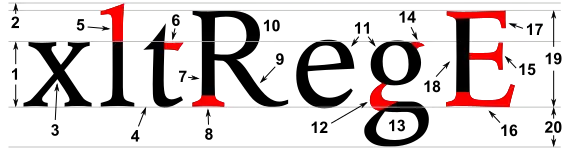
Линии
Через любую строку текста можно провести несколько воображаемых горизонтальных линий:
- Верхний край кегельной площадки — в металлическом наборе является верхней границей литеры. В компьютерных шрифтах верхний край кегельной площадки первой строки является верхним краем блока текста. В некоторых шрифтах, чаще всего декоративных, выносные элементы могут выходить за пределы верхнего края кегельной, однако такие выносные элементы требуют специальных инструкций для сопряжения с элементами верхней строки, во избежание наложений. Расстояние от верхнего до нижнего края кегельной площадки называется кеглем шрифта[1].
- Линия верхних выносных (2) — линия, проходящая через вершины верхних выносных элементов, если они унифицированы по высоте. В некоторых шрифтах может совпадать с линией прописных, но чаще — выше её[2].
- Линия прописных — линия, проходящая по верхней границе прописных букв[3]. Расстояние от базовой линии до линии прописных называется ростом прописных (19).
- Линия строчных — линия, проходящая по верхней границе строчных букв, не имеющих верхних выносных элементов и оптической компенсации[4]. Расстояние от базовой линии до верхней линии строчных называется ростом строчных (1).
- Базовая линия (линия шрифта) (4) — линия, проходящая по нижним границам букв, не имеющих нижних выносных элементов, свисаний и оптической компенсации[5]. Базовая линия одна для прописных и строчных букв.
- Линия нижних выносных — линия, проходящая по нижнему краю нижних выносных элементов, если они унифицированы по высоте[6].
- Нижний край кегельной площадки — нижняя граница литеры.
- Кроме горизонтальных линий, важное значение имеет ось овала — линия, проходящая вдоль наибольшего диаметра овала, либо через наиболее тонкие участки штриха. Ось овала может быть вертикальной или наклонной[7].
Штрихи
Выносные элементы
- Верхний выносной элемент (5) — выносной элемент строчной буквы, выступающий вверх за линию строчных;
- Нижний выносной элемент — выносной элемент, свисающий ниже базовой линии.
Прочие элементы
- Вершина (апекс) (3) — соединение двух наклонных штрихов либо наклонного и вертикального штриха, образующее угол либо имеющее ровную площадку[10];
- Горизонтальный элемент (6) — штрих, расположенный поперёк вертикального штриха. Может быть соединён с ним по краям либо в середине[11];
- Овал — округлый элемент штриха замкнутой формы, например в буквах «О», «Ю». Ось овала может быть прямой или наклонной[12];
- Полуовал (10) — может быть как замкнутым и ограниченным с одной из сторон штрихом (в буквах «Р», «Б»), так и разомкнутым (например, в букве «З»)[13];
- Узел — соединение в одном месте нескольких штрихов[14]
- Перекладина (15) — Горизонтальный штрих примерно (оптически) на середине высоты букв[15];
- Кегельная площадка — в металлическом наборе — площадка на ножке литеры, на которой располагался отпечатываемый знак. В цифровом наборе кегельная площадка — абстрактный прямоугольник, очерченный вокруг знака[16].
- Концевой элемент — окончание штриха, не имеющее засечки[17];
- Нога (9) — Наклонный штрих, заканчивающийся засечкой или концевым элементом;
- Засечка (сериф) (8) — короткий штрих, перпендикулярный основному, расположенный на его конце[18];
- Наплыв (11) — утолщение штрихов в овальных элементах[19];
- Присоединение — штрих, соединяющий части глифа[20]
- Ухо (14) — элемент, характерный для строчной буквы «g» в некоторых начертаниях. Выглядит как небольшой отросток на овале[21];
- Капля — каплевидное окончание штриха[22];
- Петля (13) — нижний элемент строчной буквы «g» в некоторых начертаниях[23]. Как и овал, имеет замкнутую форму, но построен по другому принципу;
- Хвост — элемент глифа, плавный по форме, не заканчивающийся засечкой, и являющийся, как правило, выносным[24].
Пустое пространство
- Заплечики — пространство над и под очком литеры[25];
- Внутрибуквенный просвет — внутренняя часть знака, ограниченная со всех, или почти со всех сторон другими элементами знака[26].
- Ловушка — пустая впадина на вершине острого внутреннего угла. Изначально оно было призвано компенсировать огромное растискивание, сейчас — также выровнять оптическую плотность, особенно на низких DPI.
Характеристики шрифта
- Рост строчных — высота от базовой линии до линии строчных[27];
- Рост прописных — высота от базовой линии до линии прописных[28];
- Рост шрифта — расстояние от основания литеры до печатающей поверхности. Имеет смысл только по отношению к шрифтам металлического набора, где эта величина стандартизирована и всегда равна 25,1012 мм[29];
- Очко шрифта — понятие, характеризующее рост строчных букв относительно размера литеры. Обычно не имеет величины, употребляются понятия «крупное очко» и «мелкое очко»[30].
- Контраст — характеристика различия толщин основных и соединительных штрихов шрифта[31];